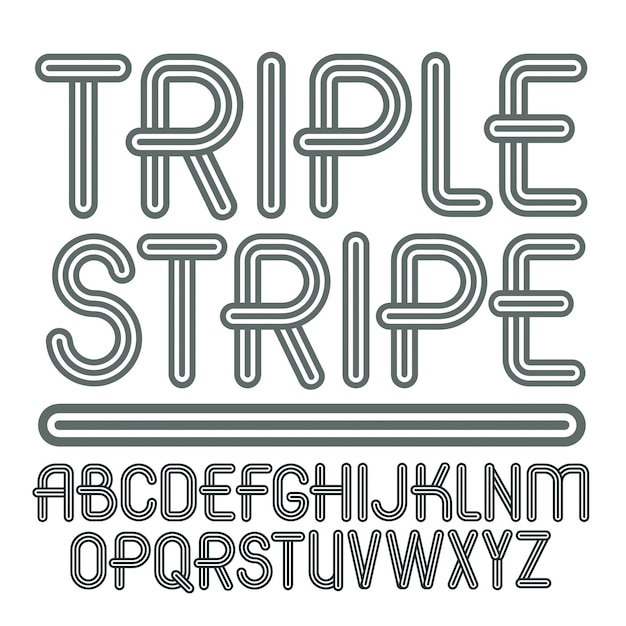
Коллекция векторных модных ретро прописных букв алфавита. Для создания логотипа можно использовать шрифт диско, шрифт от а до я. Сделано с геометрическими параллельными тройными линиями.Коллекция векторных модных ретро прописных букв алфавита. Для создания логотипа можно использовать шрифт диско, шрифт от а до я. Сделано с геометрическими параллельными тройными линиями.
Коллекция векторных модных ретро прописных букв алфавита. Для создания логотипа можно использовать шрифт диско, шрифт от а до я. Сделано с геометрическими параллельными тройными линиями.